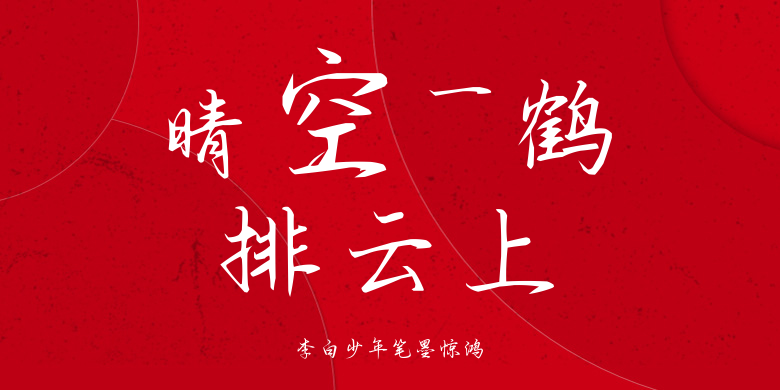
李白少年笔墨惊鸿
李白少年笔墨惊鸿,这款字体结构工整、笔画清晰,兼顾美观与易读性,适用于标题、正文、海报、包装、LOGO 等多种场景。字形优雅稳定,风格百搭耐看,适配日常排版与创意设计,让文字呈现更舒适、更具质感。李白少年笔墨惊鸿一笔一画,皆是细节,以均衡的比例、流畅的线条打造舒适视觉体验,字形端正大气,风格简约现代。无论是商业设计、品牌宣传还是日常排版,都能轻松驾驭,让文字更有格调与力量。李白少年笔墨惊鸿字体下载。